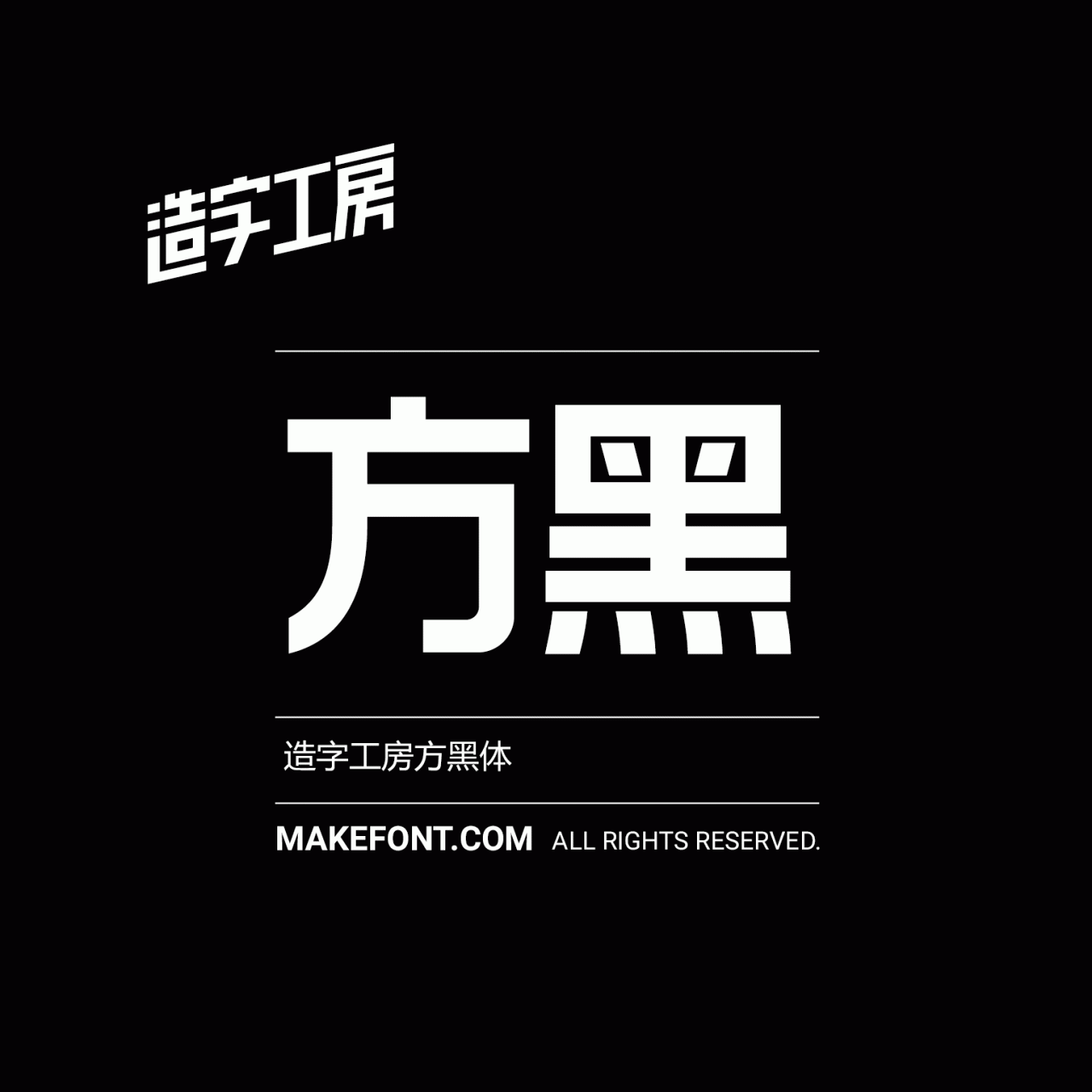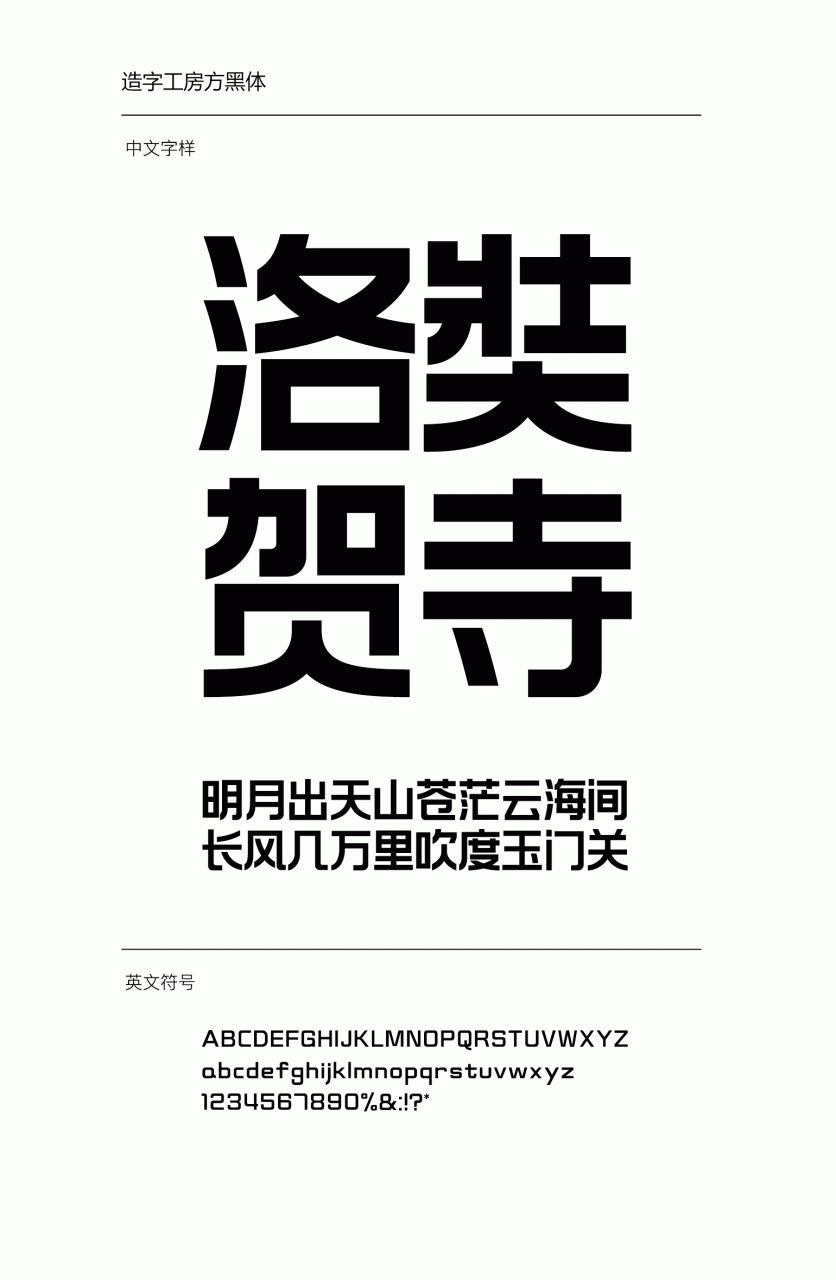
造字工房方黑常规体设计说明
造字工房方黑体在常见的黑体字形风格之上更加平稳着力,个性鲜明,笔画简洁、大方,引人注目。字形结构严谨,实用性强,横竖笔画基本保持一致,凸显出精简精干的特点。适用于标题、广告或副标题用字。本字体为简体字库,采用OpenType/CID格式,Adobe-GB1-5编码。基于中华人民共和国GB2312-80字符集标准,另按需添加101个汉字。共收容字数6864CJK汉字,ASCII常用字符100个。